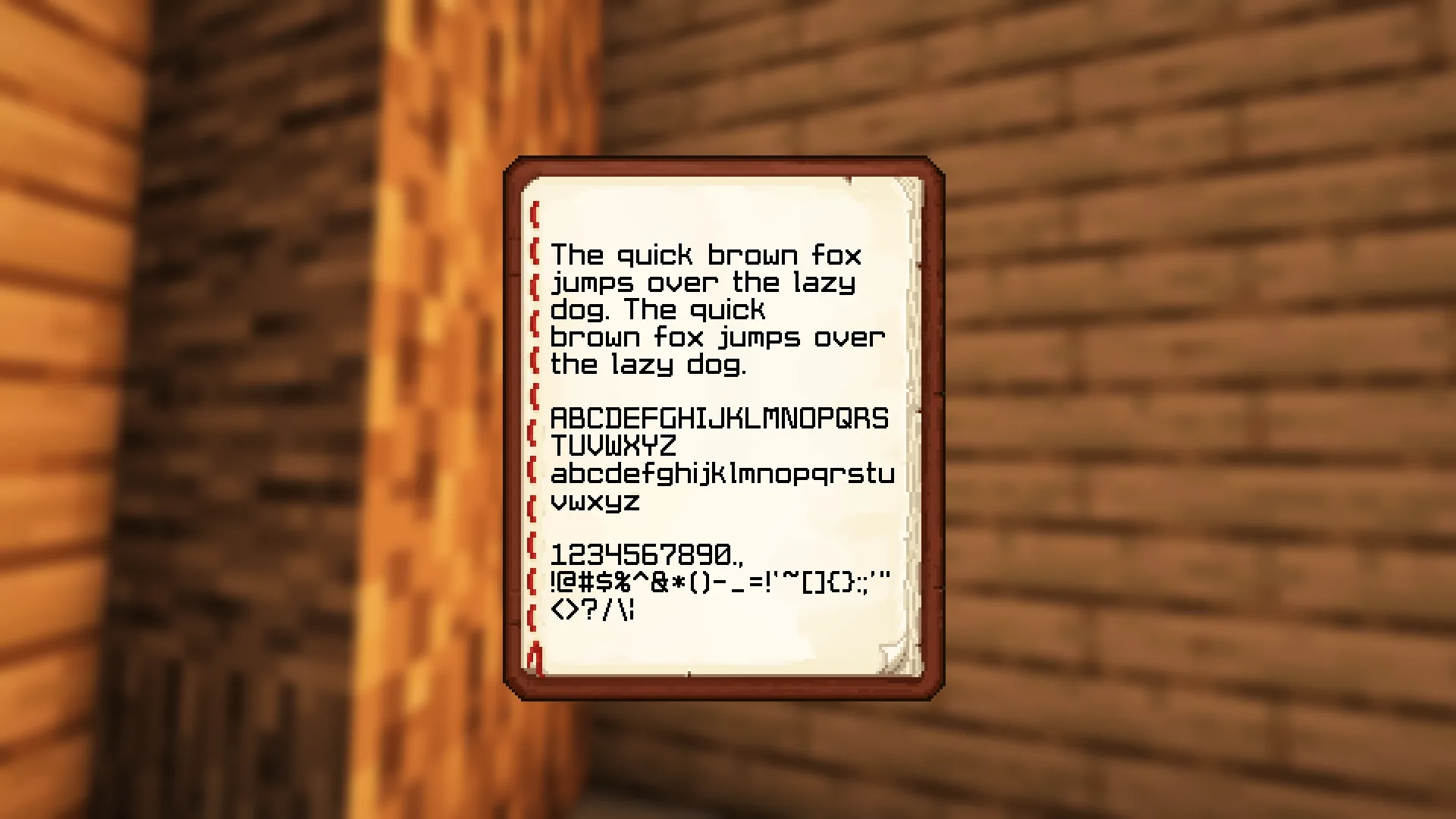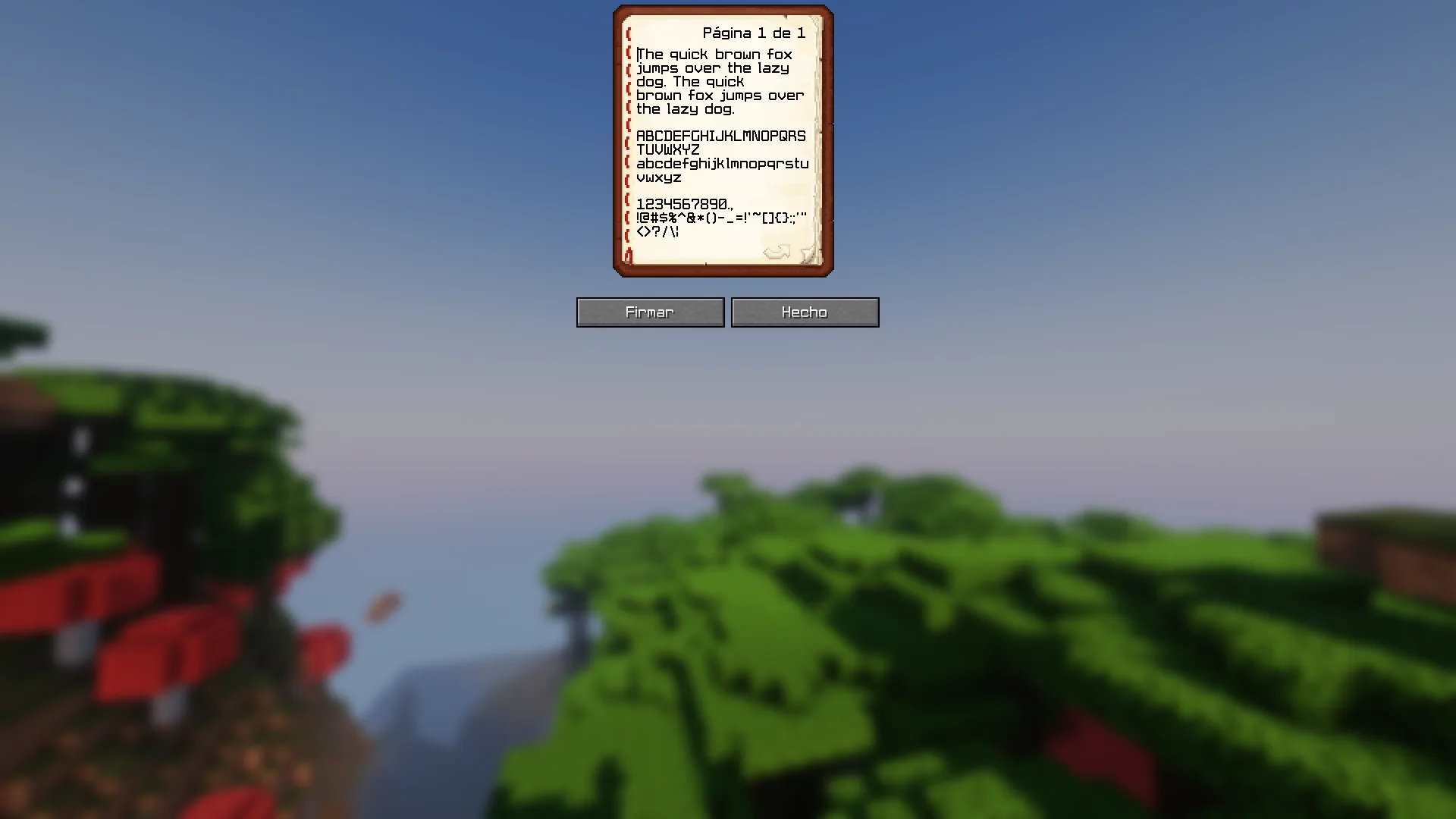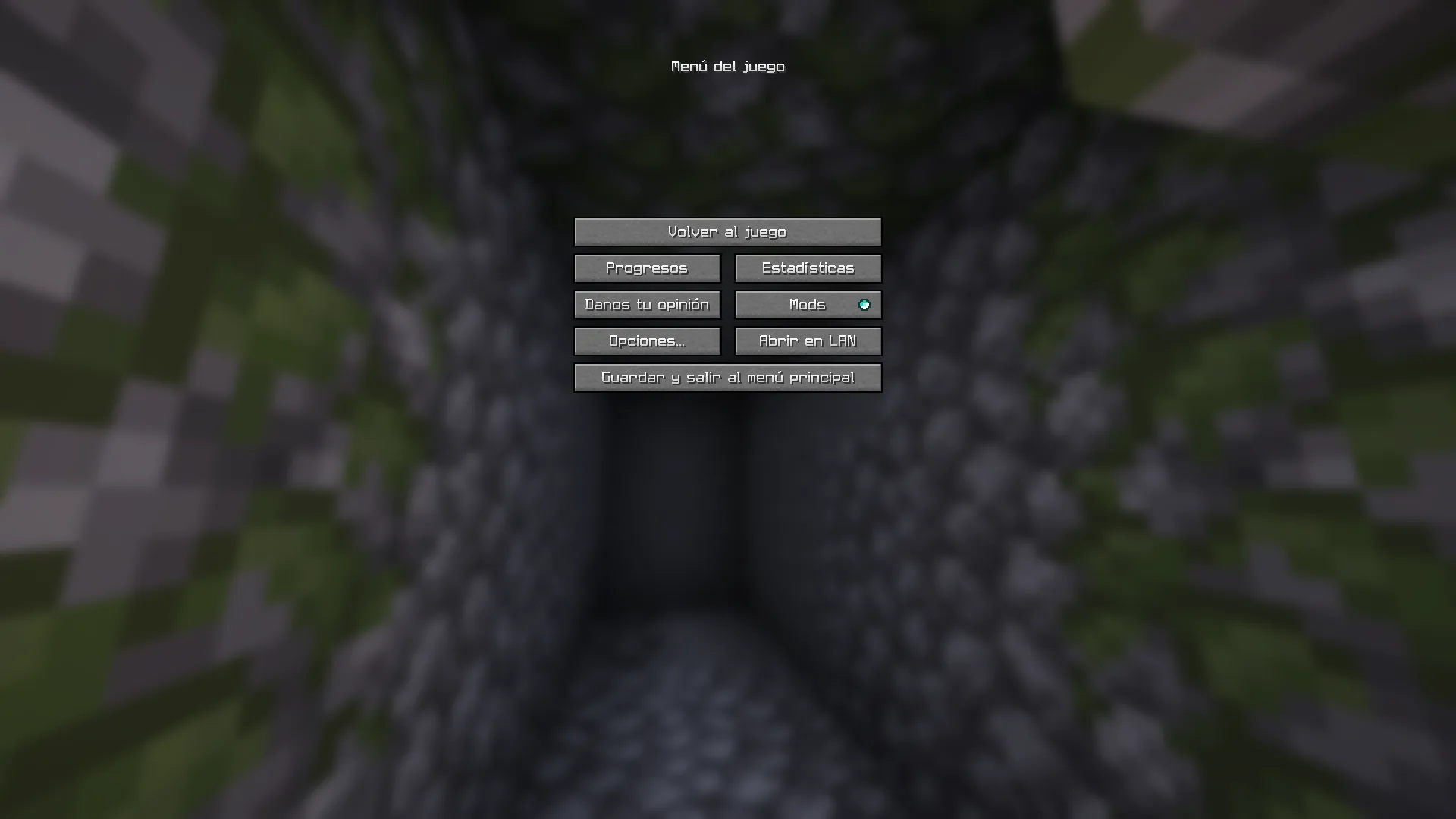
Cool Font "finished"
Завершённая версия PvP шрифта "Cool Font" заменяет стандартный шрифт в Minecraft на современный и стильный, улучшая читаемость текста в игре.
Этот ресурспак представляет собой завершённую версию шрифта "Cool Font", предназначенного для PvP. Он заменяет стандартный внутриигровой шрифт на современный и стильный шрифт, делая текст более чётким и эстетичным, особенно во время напряжённых сражений.
Cool Font "finished" улучшает весь интерфейс Minecraft, включая меню и чат, предлагая более чистый и отполированный визуальный опыт. Шрифт сочетает стиль и читаемость, обеспечивая сбалансированное восприятие текста в игре.